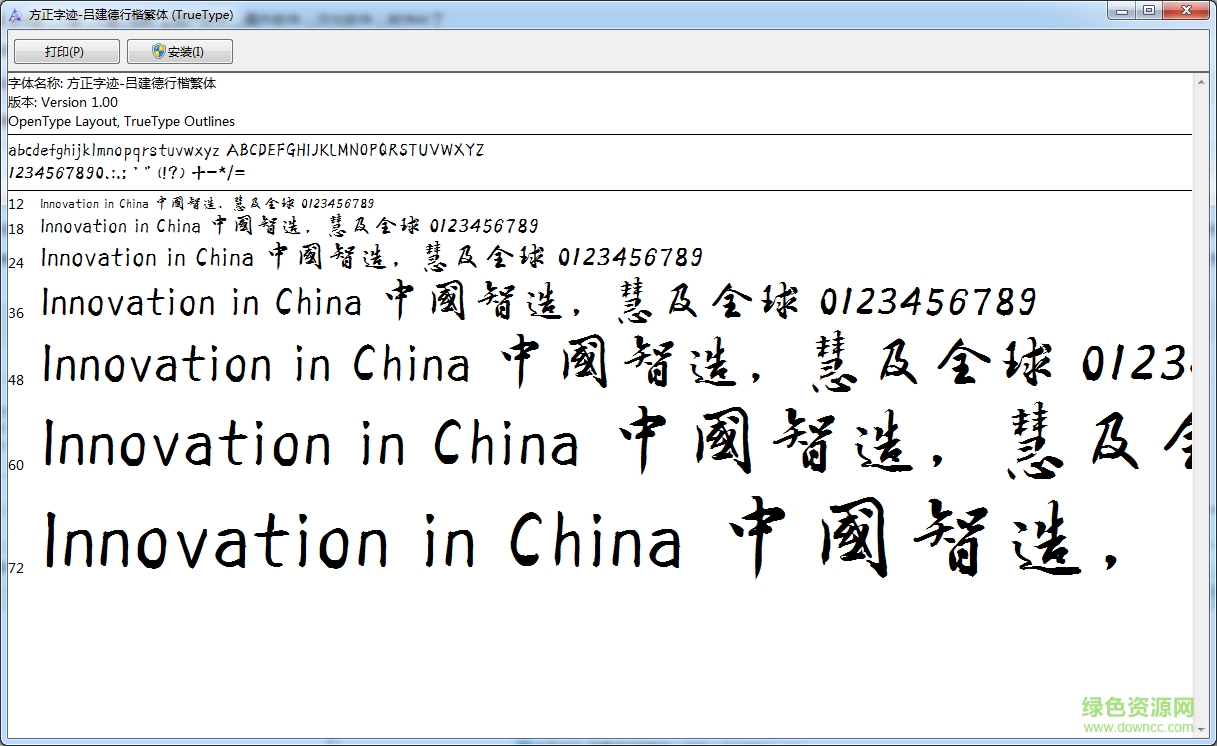
繁體行楷字庫包含了方正行楷繁體、呂建德行楷繁體、曾正國行楷繁體、漢儀行楷繁等多款常用的行楷字體,大氣俊秀,十分好看,可以用在影視海報、電子手稿等方面,需要繁體字體的朋友快來免費下載安裝吧!
1.寫行楷的過程中,個別時候由于連帶的需要,加上個別筆畫的合并、替代和減省,很多筆畫自然地連在一起書寫,筆數(shù)會比楷書有所減少。
2.而行楷的用筆則靈活、方便,一般不需要逆鋒、頓筆、停筆等嚴格的運筆,不強調(diào)用筆中更多的提按、筆畫形態(tài),只要求筆道流暢,使轉(zhuǎn)合理,行筆巧妙。